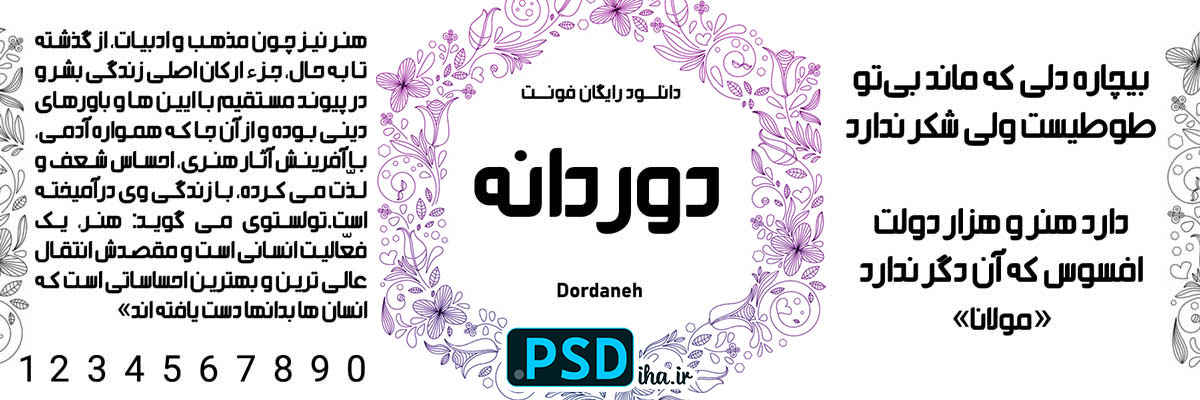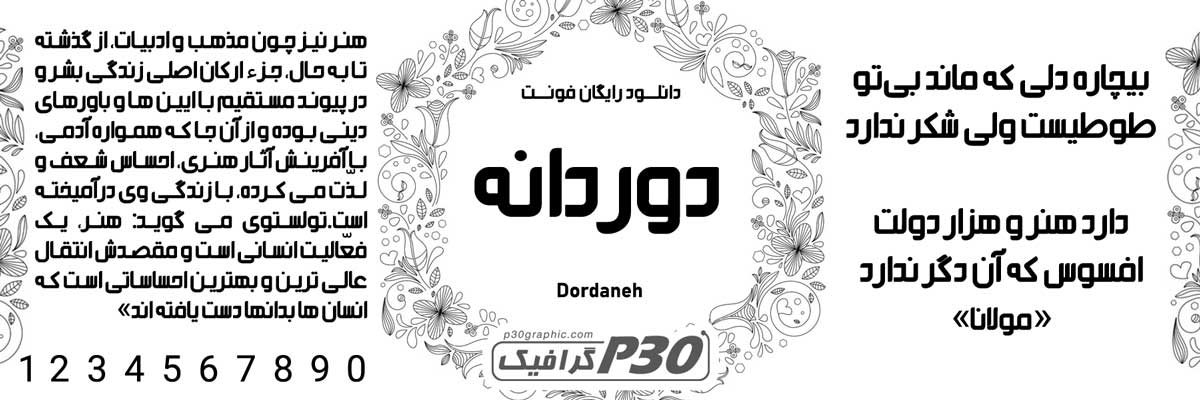
فونت دوردانه – خاص و لاکچری برای تیترهای کوتاه
اگه به دنبال فونتی هستید که یک کلمه یا یک جمله کوتاه را به الماس طرحتان تبدیل کند، فونت دوردانه همان گمشده شماست. طراحی منحصربهفرد و درامداری که برای کارت ویزیت برندهای لوکس، دعوتنامههای مجلسی، لیبل عطر و جواهرات، یا پوستر تیتر جشنها مثل نگین میدرخشد. این فونت برای متنهای بلند مناسب نیست، اما در همان نگاه اول، حسابی مخاطب را میخکوب میکند.
من خودم برای فصل تخفیف طلافروشیها و صفحات کلید واژه فروشگاههای اکسسوری، فقط از دوردانه استفاده میکنم. اگر فونتهای خاص و تیتری دیگری هم میخواهید، سری به آرشیو کامل فونتهای سایت بزنید.